Việc download font Khmer chuẩn Unicode là yêu cầu bắt buộc khi designer thực hiện các dự án thiết kế tem nhãn hàng xuất khẩu sang thị trường Campuchia, bao bì thực phẩm hoặc các ấn phẩm truyền thông đa ngôn ngữ. Khác với hệ chữ Latinh, chữ Khmer (tiếng Campuchia) có cấu trúc nét uốn lượn phức tạp và hệ thống ký tự đặc thù, đòi hỏi phông chữ phải có độ tương thích cao để không bị lỗi hiển thị. Doozypack.vn chia sẻ link tải font Khmer Unicode trọn bộ, giúp bạn sở hữu thư viện phông chữ sạch, sắc nét để hiện thực hóa các bản in chuyên nghiệp nhất.
Phân loại các nhóm font chữ Khmer phổ biến nhất hiện nay
Trước khi bắt đầu tải font chữ Khmer Unicode, bạn cần xác định rõ phong cách thiết kế để lựa chọn nhóm font phù hợp, đảm bảo tính thẩm mỹ và độ dễ đọc cho thành phẩm bao bì.
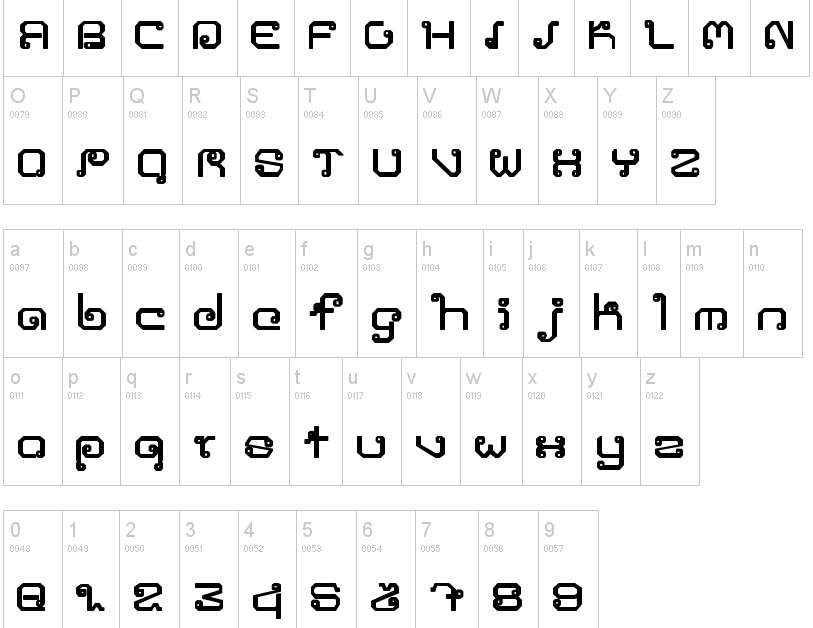
Nhóm font Khmer Unicode tiêu chuẩn (Standard)
Đây là nhóm font được sử dụng rộng rãi nhất trên các nền tảng web, văn bản hành chính và nội dung chi tiết trên bao bì. Đặc trưng của nhóm này là cấu trúc nét chữ rõ ràng, minh bạch và hỗ trợ bảng mã Unicode quốc tế 100%. Các tên font tiêu biểu như: Khmer OS, NiDA, hoặc Hanuman giúp thông tin bảng thành phần, địa chỉ sản xuất trên vỏ hộp hiển thị vô cùng sắc nét.
Nhóm font Khmer trang trí và tiêu đề (Display & Header)
Nếu bạn đang tìm kiếm download font khmer free để làm Logo hoặc tiêu đề chính cho các chiến dịch marketing, nhóm font trang trí với các nét vẽ cách điệu, mập mạp hoặc thanh mảnh nghệ thuật sẽ là lựa chọn lý tưởng. Những phông chữ này giúp tiêu đề bao bì thu hút thị giác mạnh mẽ và tạo dấu ấn thương hiệu sâu đậm đối với người tiêu dùng tại bản địa.
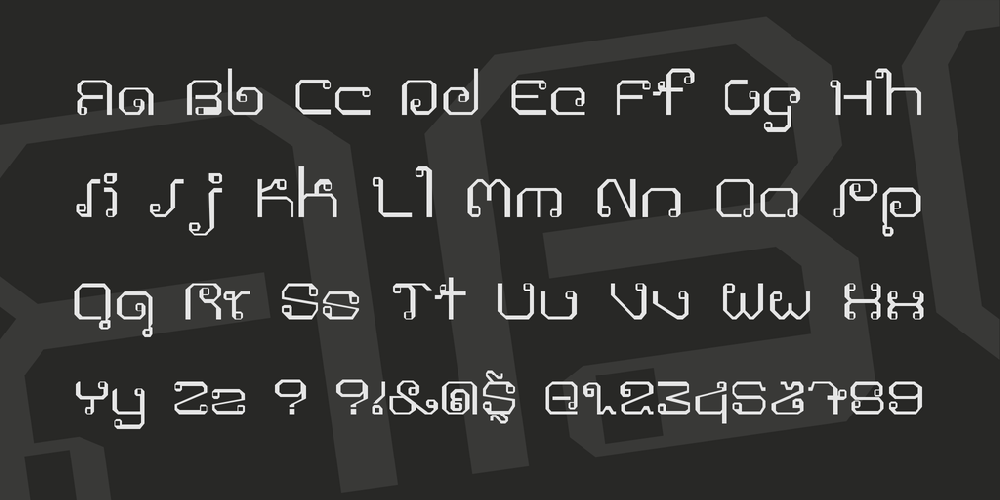
Tư vấn từ xưởng in: Để đảm bảo tính hiển thị tốt nhất trên mọi thiết bị và máy in công nghiệp, Doozypack.vn khuyên bạn luôn ưu tiên tải font khmer unicode. Đây là tiêu chuẩn vàng giúp ngăn chặn lỗi hiển thị “ô vuông” hoặc sai lệch vị trí các ký hiệu phụ trong chữ Khmer.
03 Ứng dụng của font chữ Khmer trong thiết kế bao bì xuất khẩu
Thị trường Campuchia là điểm đến tiềm năng của nhiều thương hiệu Việt, và phông chữ đóng vai trò “cầu nối” văn hóa vô cùng quan trọng:
- Tem nhãn thực phẩm & Mỹ phẩm: Sử dụng tải font khmer chuẩn giúp người tiêu dùng bản địa dễ dàng tra cứu thông tin sản phẩm, tạo niềm tin về sự chuyên nghiệp của thương hiệu.
- Hộp giấy quà tặng: Sự kết hợp giữa font Khmer nghệ thuật và các phương pháp gia công như ép kim vàng, phủ UV định hình tại Doozypack.vn giúp bao bì trở nên sang trọng và đẳng cấp.
- Túi giấy doanh nghiệp: In tên công ty bằng font Khmer sắc nét trên túi giấy Ivory giúp khẳng định quy mô và sự tôn trọng đối với thị trường mục tiêu.
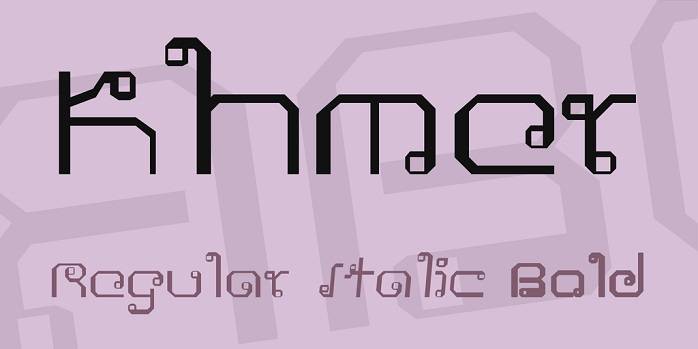
Lưu ý kỹ thuật khi in ấn tem nhãn chữ Khmer tại Doozypack.vn
Sản xuất bao bì sử dụng hệ chữ uốn lượn như tiếng Khmer đòi hỏi designer cần lưu ý một số vấn đề kỹ thuật tại xưởng in chuyên nghiệp:
- Kiểm soát các ký hiệu phụ (Subscripts): Chữ Khmer có các nét chân (Coeng) và ký hiệu nằm dưới hoặc trên thân chữ chính rất nhỏ. Khi in trên giấy thô nhám như giấy Kraft, hãy để size chữ tối thiểu 8pt để các nét này không bị bít mực.
- Hệ màu CMYK cho văn bản: Luôn thiết kế trên hệ màu CMYK. Đối với chữ Khmer màu đen nhỏ, hãy sử dụng thông số K=100 để chữ sắc nét nhất, tránh hiện tượng nhòe màu do lé bản kẽm khi in chồng nhiều bản màu.
- Quy tắc Convert Font: Đây là bước quan trọng nhất. Để tránh việc xưởng in bị thiếu font dẫn đến hiện tượng nhảy chữ, bạn hãy luôn lệnh Create Outlines (Ctrl+Shift+O) cho toàn bộ nội dung chữ Khmer trước khi gửi file thiết kế cho Doozypack.vn.